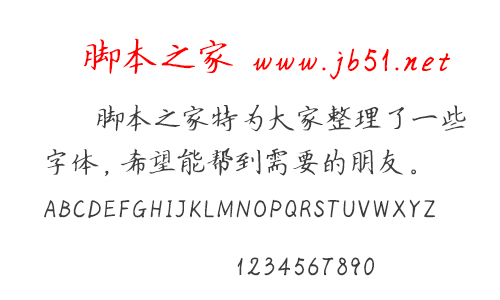
笑看百世間是思雨字庫(kù)推出的一款個(gè)性藝術(shù)字體,風(fēng)格比一般的字體更有特色,連貫字跡顯得干練而不凌亂,清新簡(jiǎn)明,具有很好的視覺(jué)感,適合應(yīng)用于藝術(shù)設(shè)計(jì)、平面宣傳設(shè)計(jì)、網(wǎng)頁(yè)設(shè)計(jì),書(shū)法字帖等領(lǐng)域,歡迎喜歡笑看百世間字體的朋友前來(lái)下載使用。